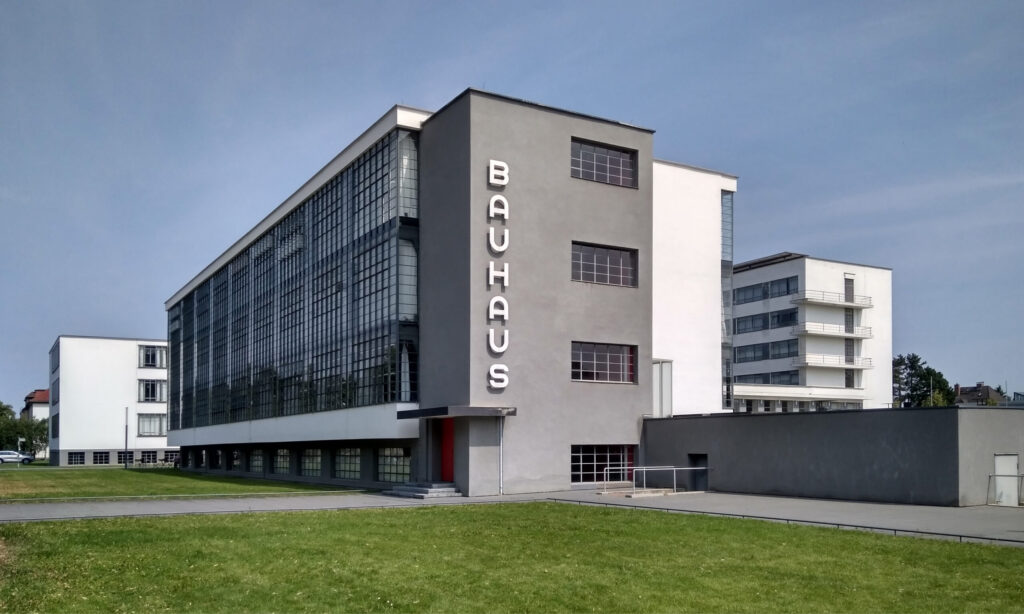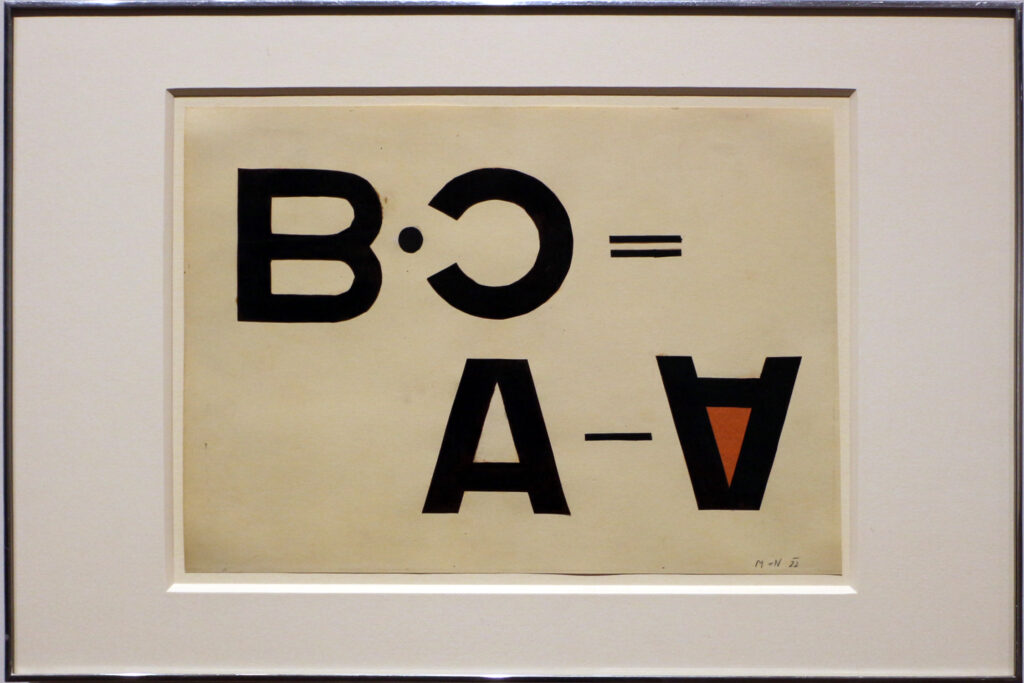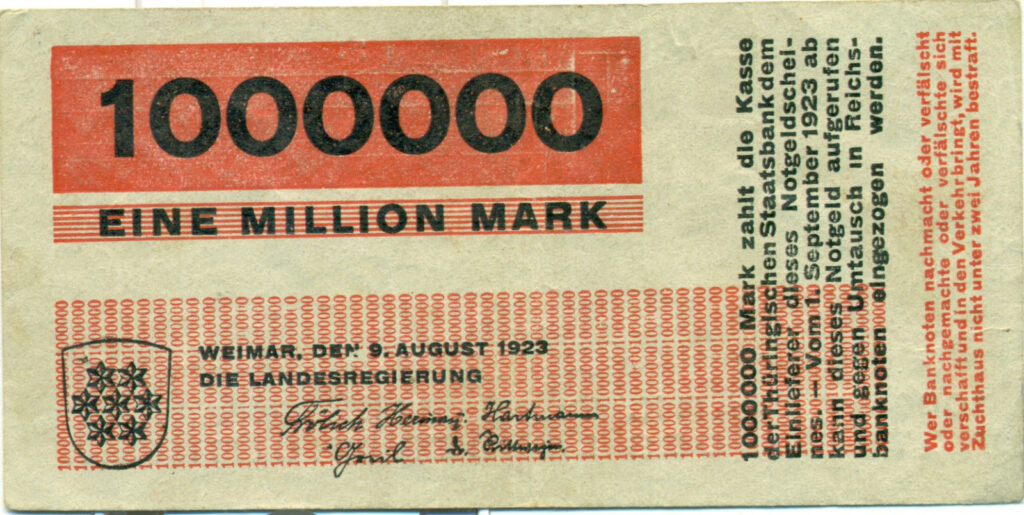
1920 – Das Bauhaus
Die 1920er-Jahre prägen Kunst, Architektur, Grafik und Typografie Mitteleuropas entscheidend. Im Zentrum steht das von Walter Gropius gegründete Bauhaus. Dessen Pädagogik strebt die Einheit von Kunst und Handwerk an – die Trennung zwischen Künstlern und Handwerkern soll aufgehoben werden. Unter dem Schlagwort „Neue Typografie“ entsteht ein modernes, funktionales Gestaltungsverständnis: Arbeit mit serifenlosen Schriften, asymmetrischem Satz, Balken und Linien, bevorzugt in Schwarz, Weiß und Rot.
Zu den prägenden Lehrern zählen Herbert Bayer, László Moholy-Nagy, Marcel Breuer, Kurt Schwitters und Karel Teige, die in der Grotesk-Typografie das Ideal der Industriegesellschaft sehen. Beispielhaft ist die von Josef Albers 1925 entwickelte Kombinationsschrift, reduziert auf geometrische Grundformen.
Eine zentrale Figur der Zeit ist Jan Tschichold, der mit seiner Schrift elementare typografie (1925) in den typografischen mitteilungen zum Wortführer der Avantgarde wird. Er plädiert für funktionale Gestaltung, die beiden Kernprinzipien folgen:
• Typografie ist zweckorientiert.
• Ihr Zweck ist Mitteilung – so klar, einfach und eindringlich wie möglich.
Von ihm stammen Schriften wie Transit, Zeus und später die Sabon (1964, auf Basis der Garamond).
Parallel entstehen serifenlose Klassiker: Paul Renners Futura (1927), eine Ikone der Moderne, und Rudolf Kochs Kabel (1927), die viele Nachfolger beeinflusst.
Doch auch die gebrochenen Schriften entwickeln sich weiter. Rudolf Koch entwirft die Deutsche Schrift und die Klingspor. Ab 1933 wird die Fraktur zur offiziellen „deutschen Schrift“ und von den Nationalsozialisten als Propagandainstrument missbraucht. 1937 verbietet man jüdischen Verlagen ihre Verwendung, 1941 erfolgt jedoch ein radikaler Bruch: In einem Erlass wird die Fraktur als „Schwabacher Judenletter“ verboten, und fortan müssen alle Druckwerke in Antiqua erscheinen.
Dieser politische Missbrauch beschädigt den Ruf der Fraktur nachhaltig. Bis heute löst sie bei vielen Betrachtern die Assoziation mit dem Dritten Reich aus.